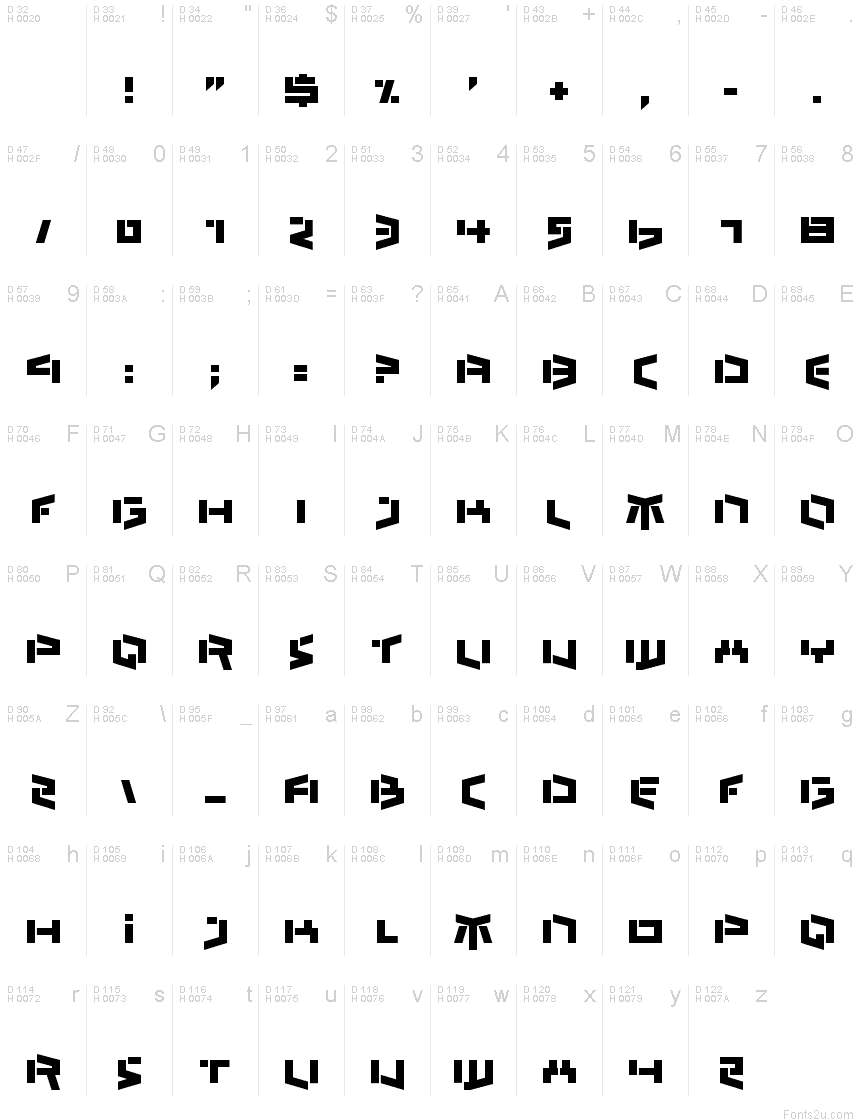
Bedlam Remix من تصميم Levi هو خط عرض (display) تقني مجاني يتميز بنبض صناعي حاد. تتشابك الحروف كأنها صفائح معدنية زاوية، مع زوايا حادة وقطع متدرج يبدو وكأنه مستوحى من واجهة ألعاب مستقبلية أو تأثيرات بصرية رقمية (glitch). المسافات بين الحروف ضيقة ومدمجة، مما يجعل الكلمات تبدو ككتل سوداء صلبة تترك أثراً قوياً بمجرد النظر إليها.
يعتبر Bedlam Remix خطاً مثالياً للنصوص القصيرة والمؤثرة: الشعارات، وعلامات الرياضات الإلكترونية، وعناوين الألعاب، والملصقات، والمنشورات الترويجية، وتصاميم الملابس الجريئة. يحقق هذا الخط المجاني أفضل النتائج عندما تحافظ على قصر الرسائل وتزيد من حجم الخط، مع موازنته بخط هندسي بلا زوائد (sans serif) من عائلة Bedlam أو بخط محايد للنصوص الجانبية.